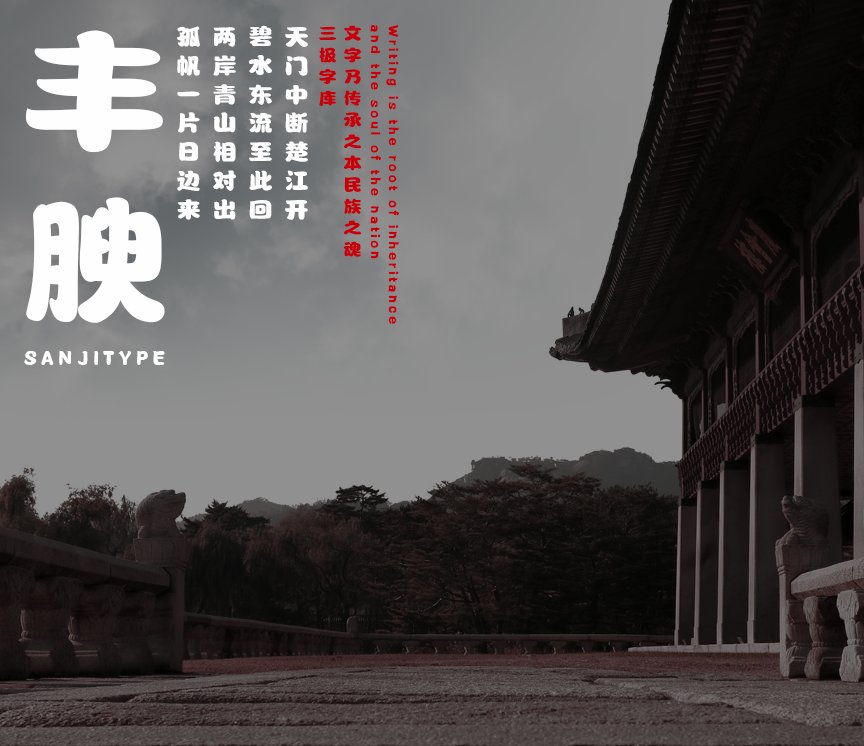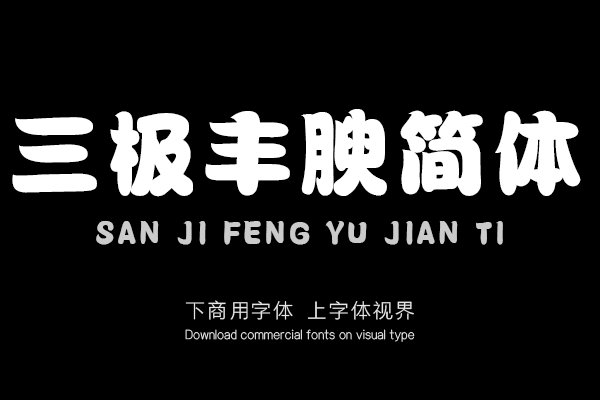
三极丰腴简体是一款用短粗笔画特征构成的创意字体,字形丰腴滋润,胖瘦得体,匀称适中。个性天真可爱,富有童趣。适用于杂志、包装和品牌广告宣传设计及标题排版、招牌设计......购买须知:“下载服务费”与“字体VIP”所获得字体 仅用于个人非商用, 商用请联系付费授权。本字体为电脑用字,手机没有root权限不支持直接手机换字(手机如何root,请自行百度搜索教程)。购买前请先 了解清楚后再付款 ,字体为虚拟产品无法回收 一旦购买不支持退款。